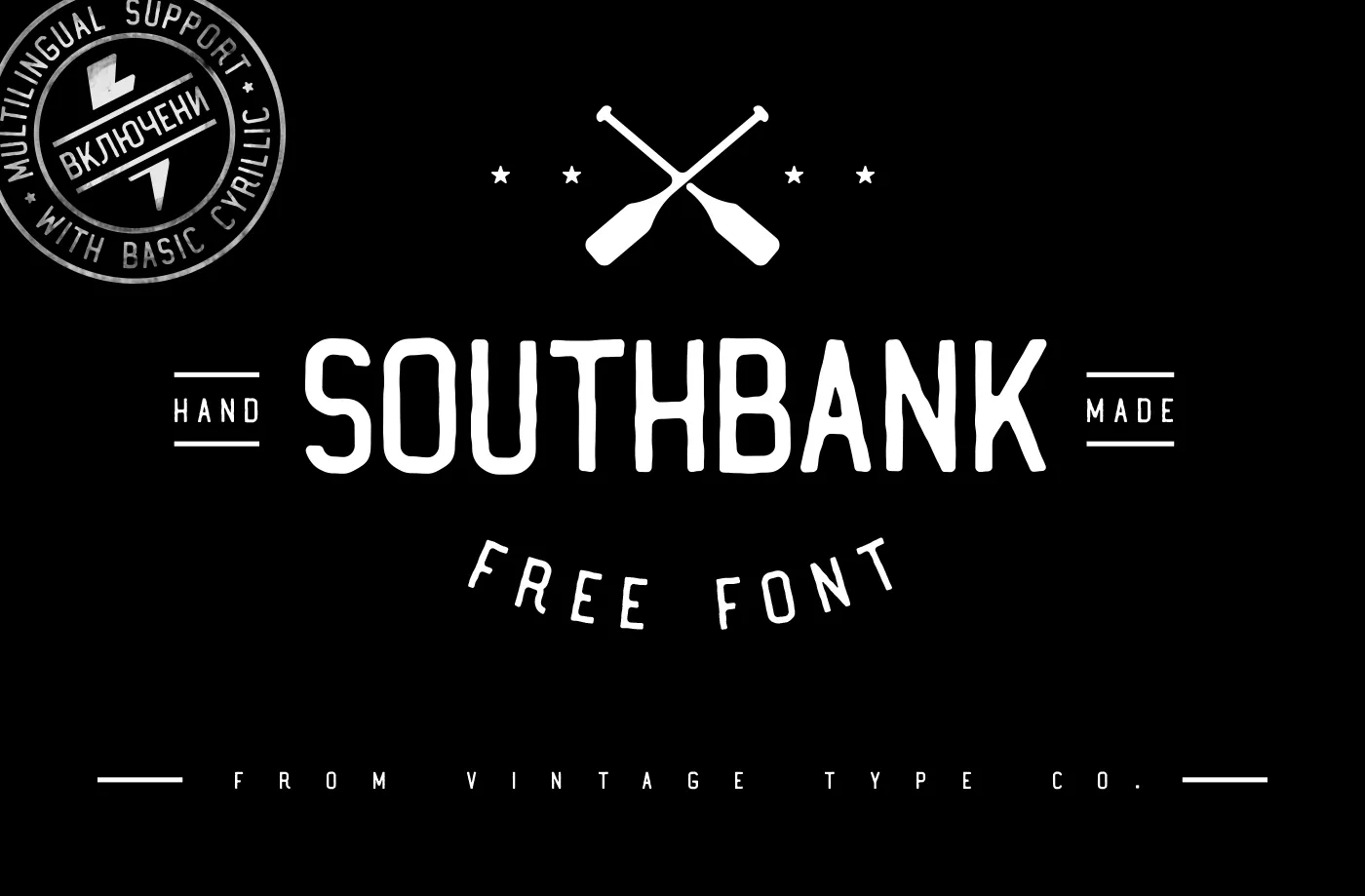
Southbank Font – Download Grátis
A Southbank Font é uma opção perfeita para quem busca um estilo visual dinâmico e vibrante para seus projetos digitais. Criada pelo designer Hamilton, essa fonte do tipo Display oferece linhas afiadas e traços definidos que destacam-se em qualquer ambiente de layout gráfico ou design editorial. Suas características agressivas e sua capacidade de criar texturas imersivas garantem uma experiência visual impactante, tornando-a ideal para headlines, marcasos promocionais ou design gráfico moderno. Não apenas será um recurso poderoso para designers digitais, mas também uma fonte atraente que destacará seu trabalho nas redes sociais e em plataformas online.